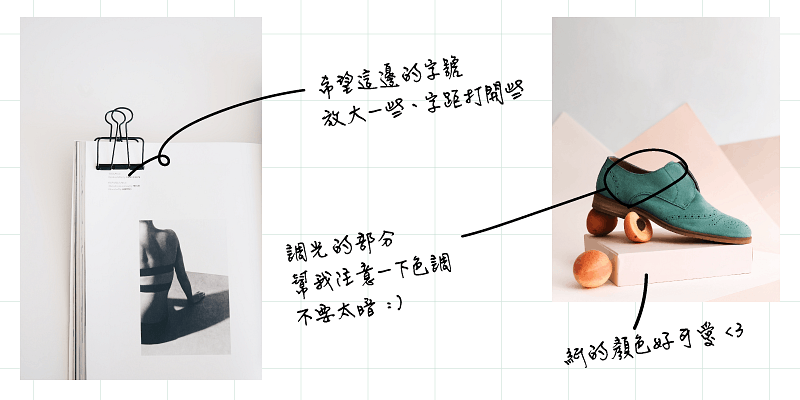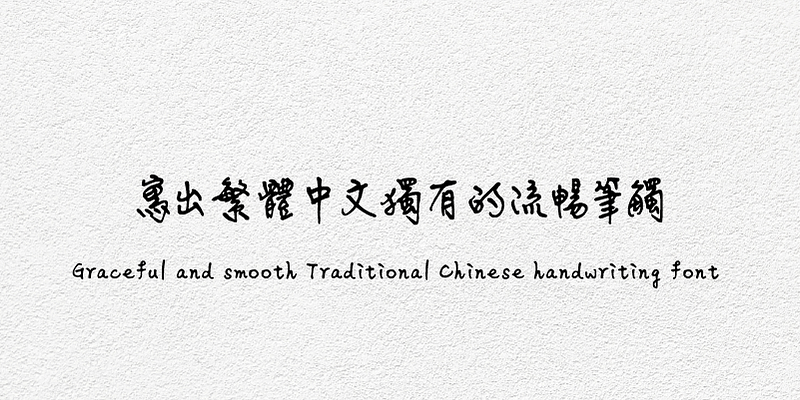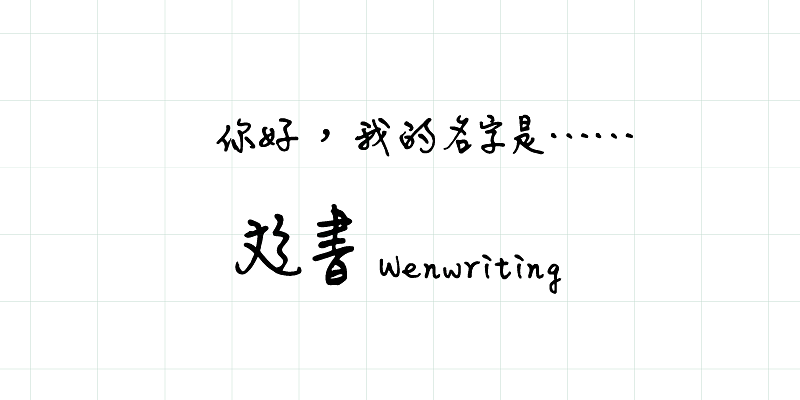
18,000개 이상의 문자로 구성된 Wenwriting 서체는 Pin-Wen Song(宋ITEM彣) 씨가 제작했습니다. 디자이너나 서예 전문가는 아니지만 송씨는 글쓰기의 세계에서 즐거움을 찾고 있습니다. 그가 개발하는 스타일은 깔끔하고 우아하며 부드러운 외관이 특징으로, 사용자에게 친근하고 매력적으로 다가옵니다. 중요한 것은 많은 중국어 번체 글꼴에는 종종 없는 문자 “彣”이(가) 송씨의 “彣書” 서체에 절대적으로 포함되어 있다는 것입니다!